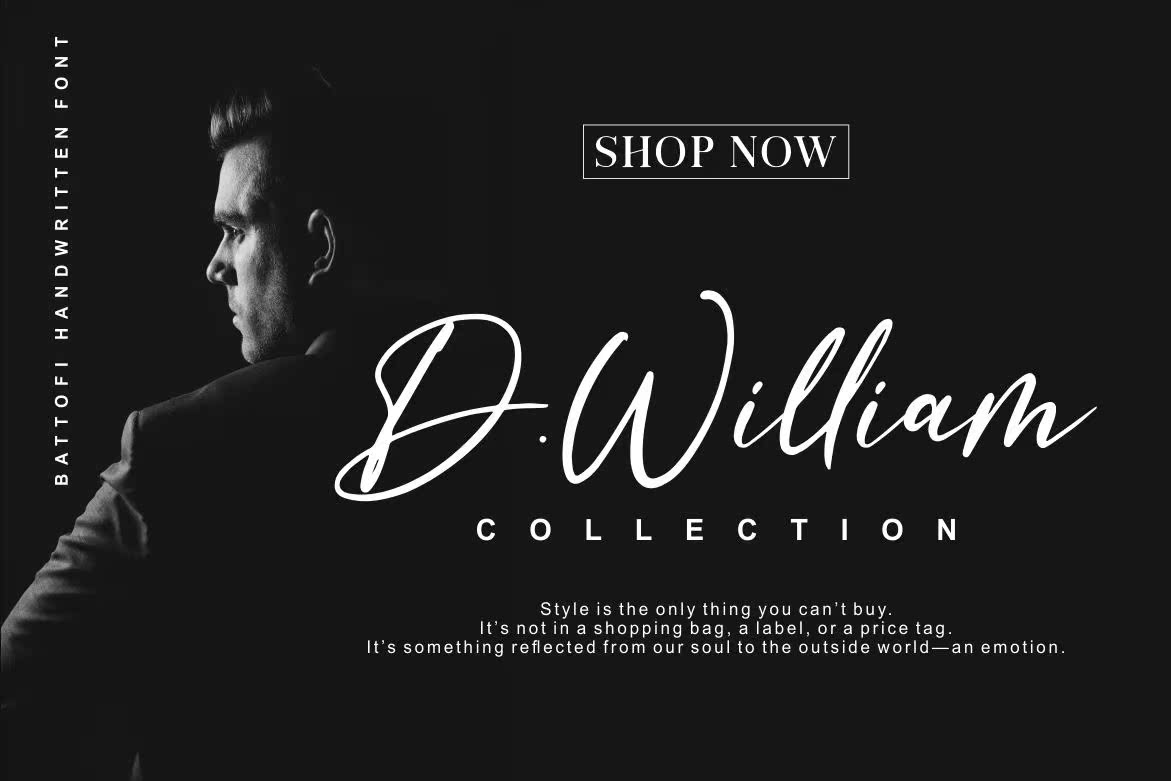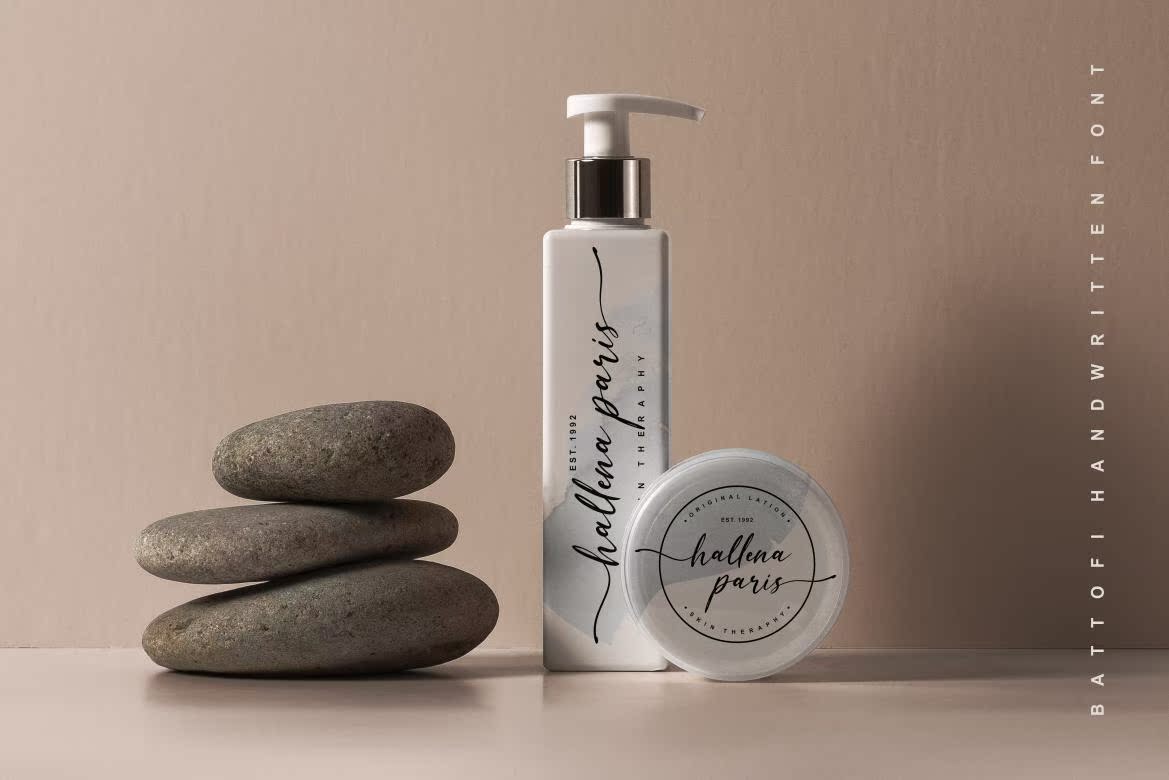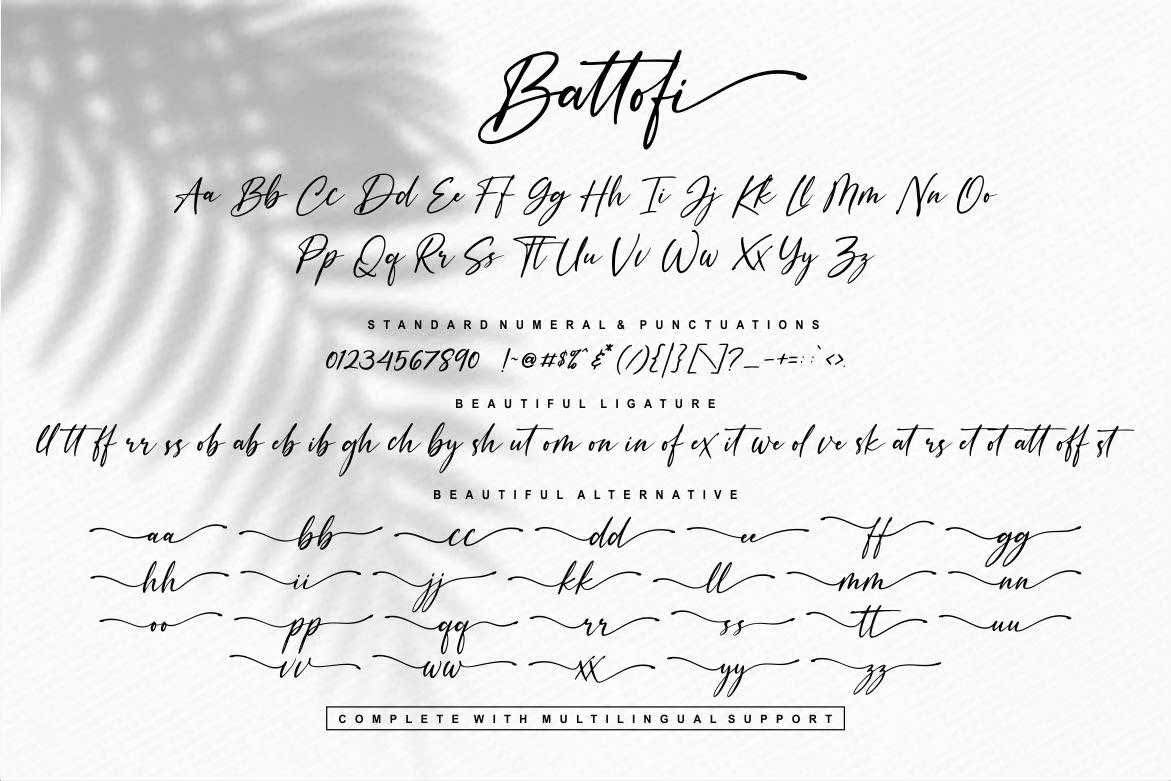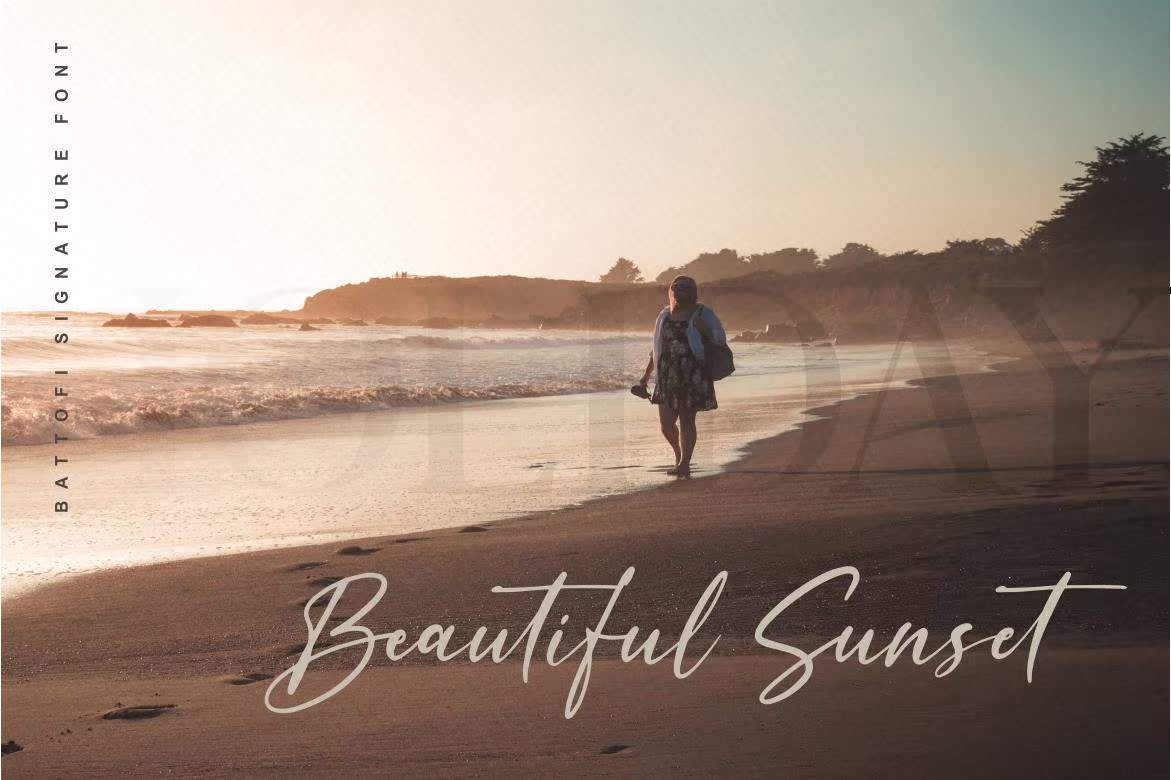
您好,,,介绍新的“Battofi”脚本字体。AbeAutifulScriptFont具有优雅的样式Extras和31连接器,可满足您的需要。通过内置的字体功能,此脚本可供您自己编写。您好,,,介绍新的“Battofi”脚本字体。AbeautifulscriptFont具有优雅的样式Extras和31连接器,以满足您的需要。借助内置的字体功能,此脚本非常适合您自己编写。